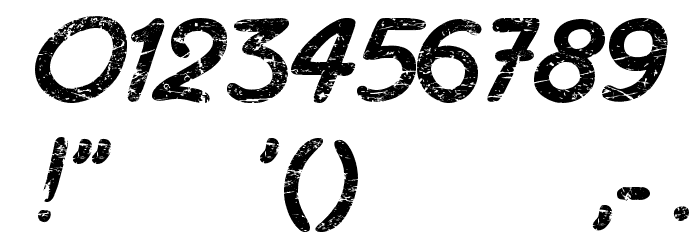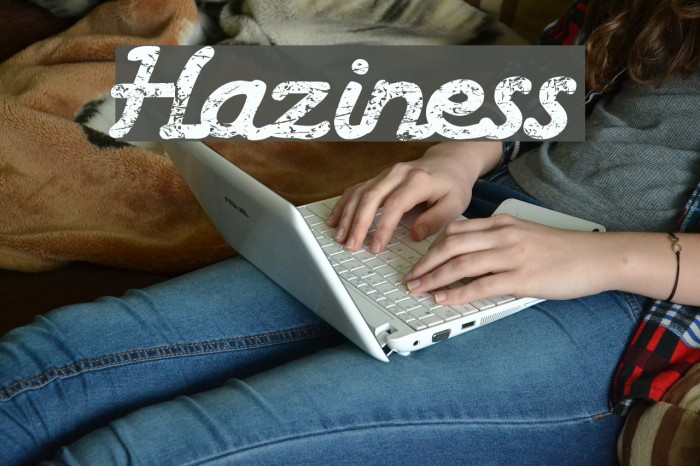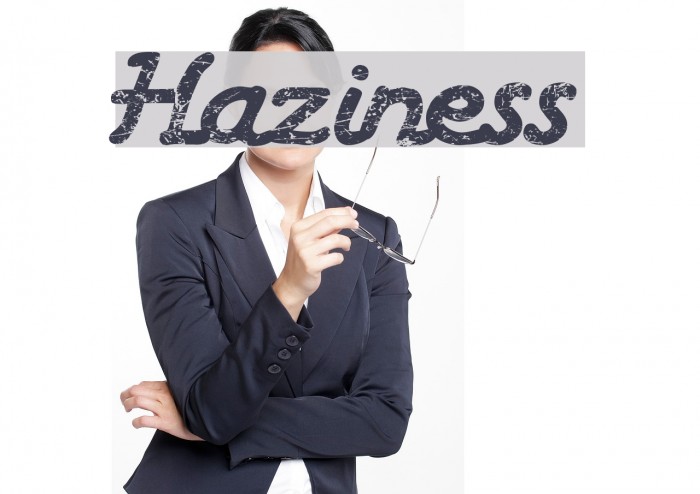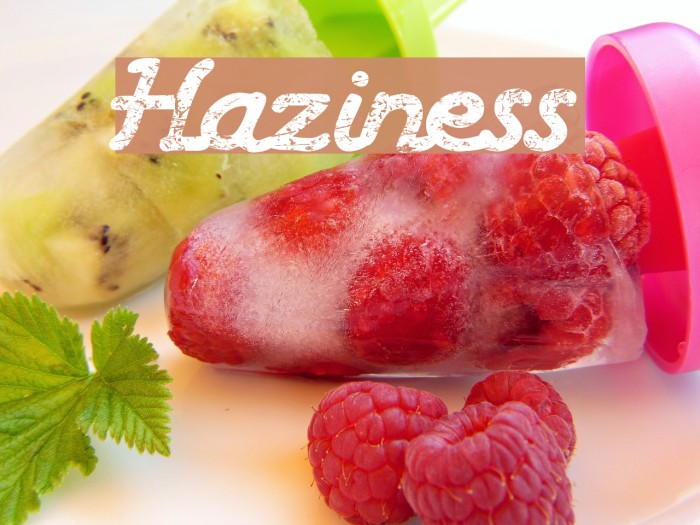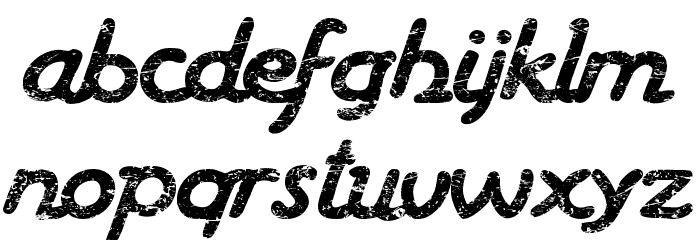
Haziness Font
| Stil general | Vintage, Decorative |
| Proiecte propuse | Ideal for album covers, posters, branding for edgy or artistic products, and any design requiring a vintage or distressed look. |